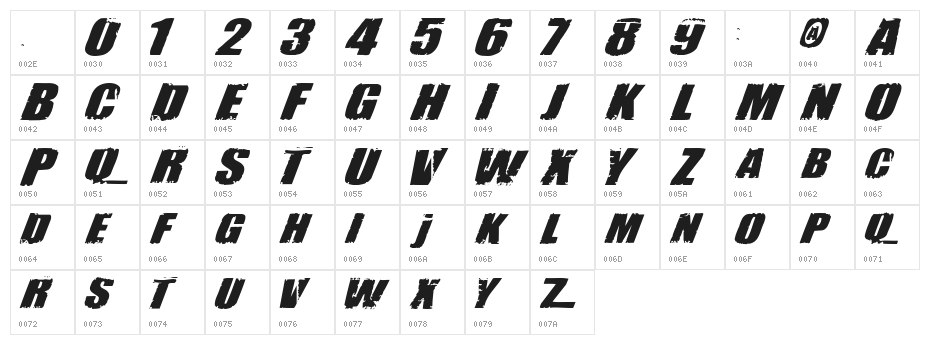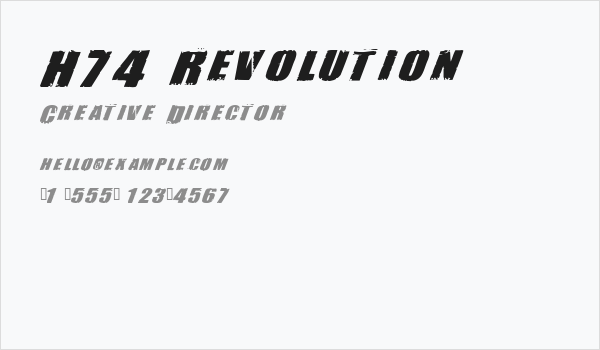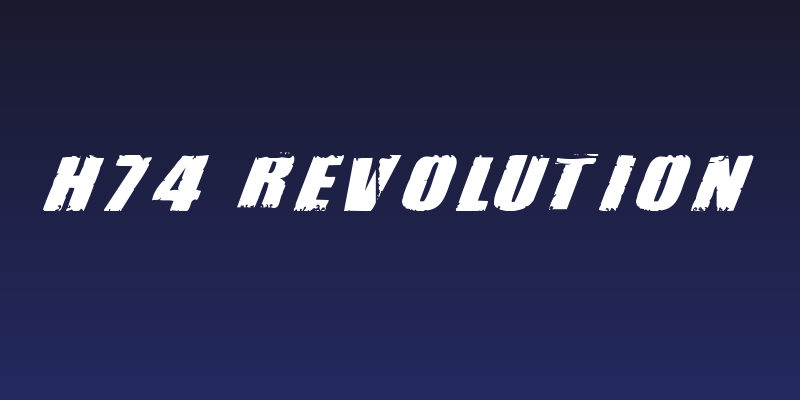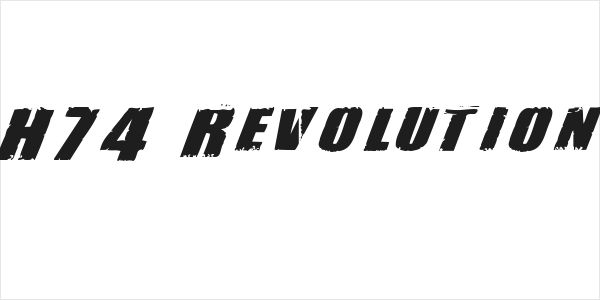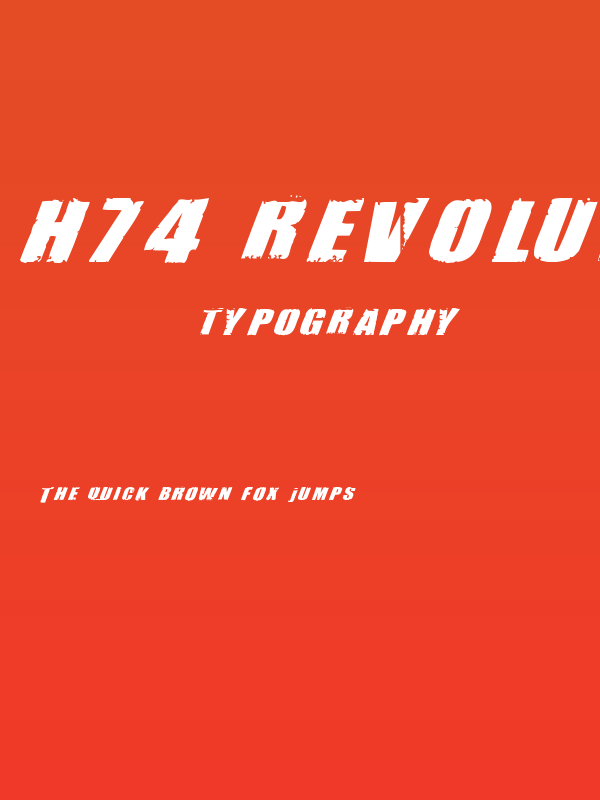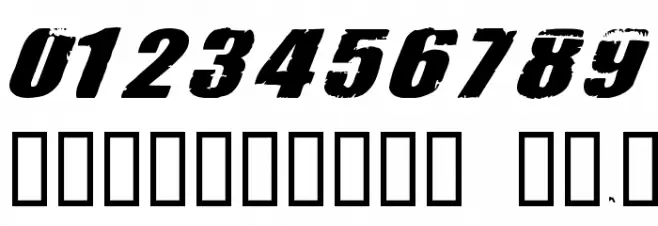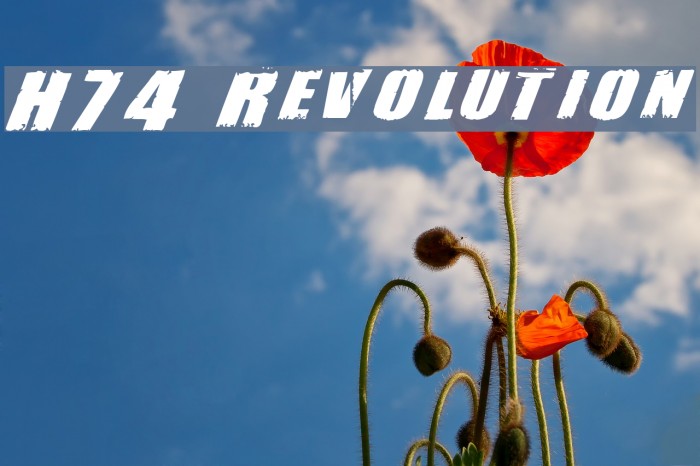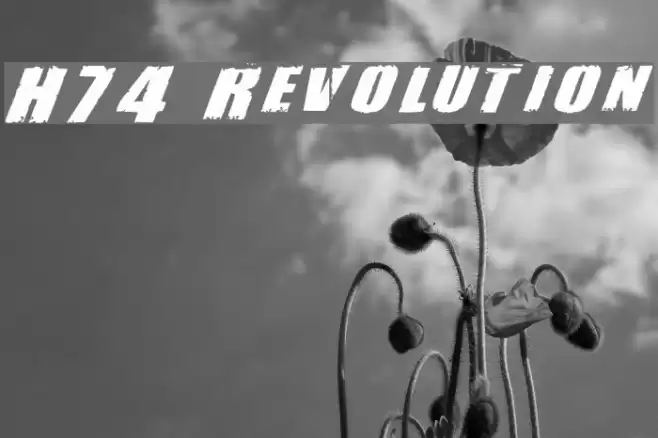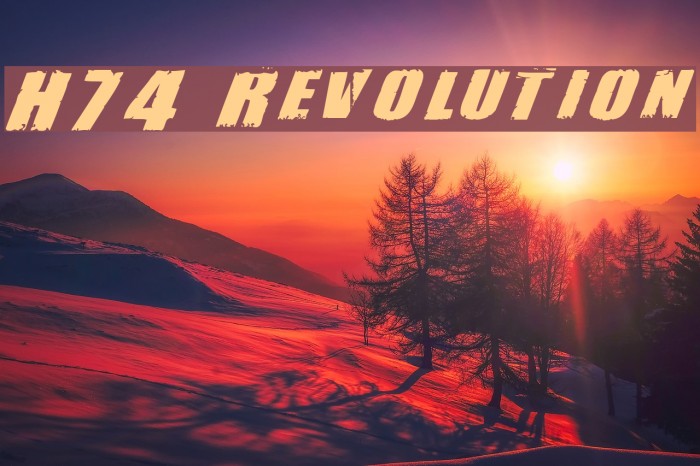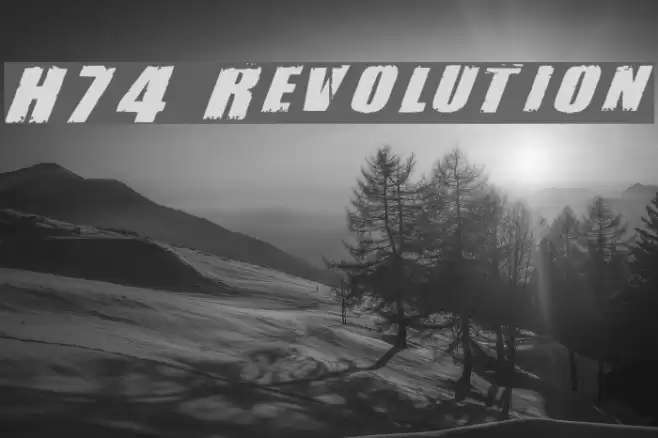
H74 Revolution Font
✎ Messy
| Категория | Messy |
| Общий стиль | Modern, Grunge |
| Рекомендуемые проекты | Ideal for music album covers, event posters, urban-themed designs, and edgy branding projects. |
| Категория | Messy |